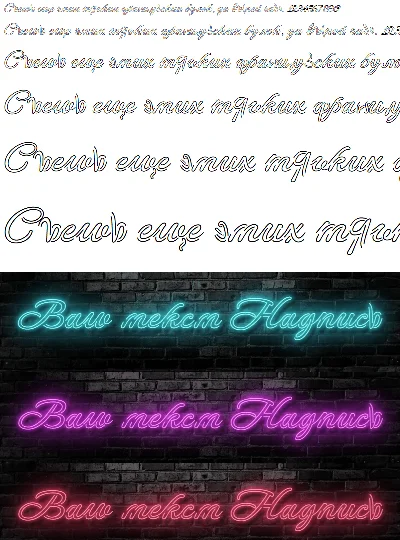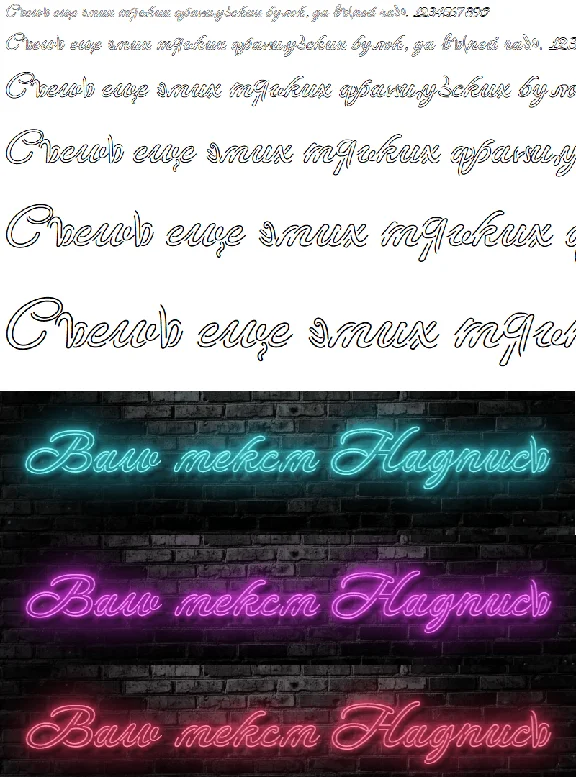
Неоновый кириллический шрифт neon cyrillic font
Крутой красивый неоновый кириллический шрифт тонкие линии.
Cool beautiful neon Cyrillic font fine lines.